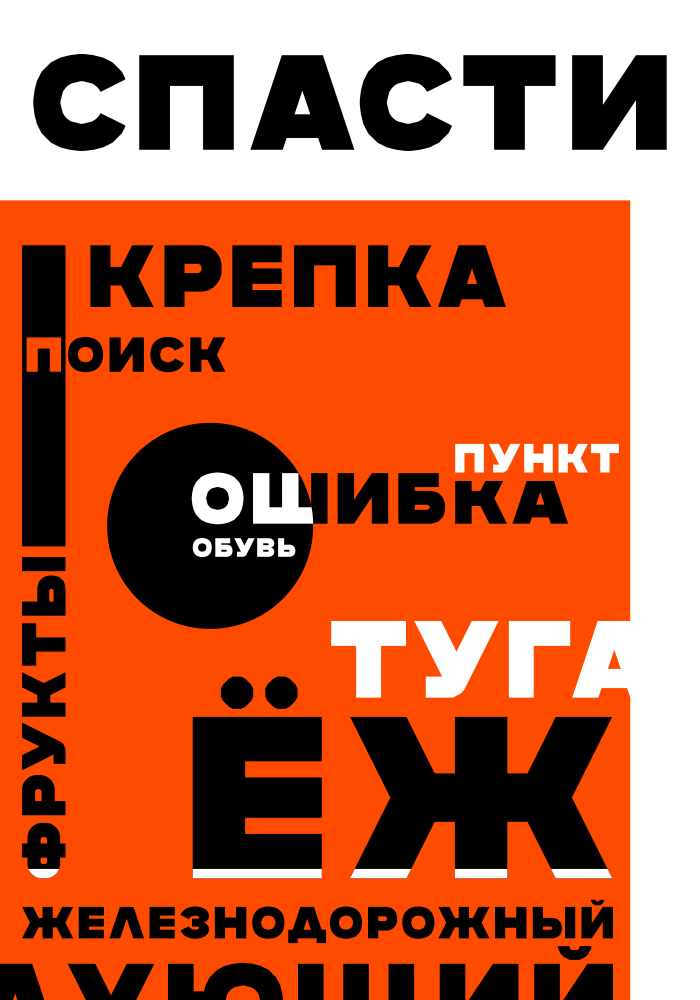
И СОХРАНИТЬ - (точнее спати и сохрани) - самая частая молитва к богу у православных (в России их много).
Я этот фильм ещё не смотрел, кстати, думаю стоит. А по шрифту - он мне очень напоминает Gotham, и чуть-чуть Proxima Nova. Но - да, он вполне конструктивистский, как и твой отличный плакат. Но крышка буквы П всё же нуждается в оптической компенсации на один пиксель - слишком сильно она выделяет и тянет вниз эту букву. Можно ещё придраться, что Ф не такая округлая, как З - но это уже придирки.
спасти
Я согласен о букве «П». Делаю ещё шрифт, в котором эта проблема и другие — исправлены. И он даже имеет латиницу.
Кстати, Dr. Dolittle не имеет ничего общего с Россией. Это просто факт, что я его посмотрел при создании этого шрифта)
Ты можешь создать латинские буквы? :)
Посмотри на «ALDRON». Оно улучшенный шрифт с латинскими буквами.
<Dmitriy Sychiov (Sychoff)> AND SAVE - (more precisely, sleep and save) - the most frequent prayer to God among the Orthodox (there are many of them in Russia).
I haven't seen this movie yet, but I think it's worth it. As for the font, it reminds me a lot of Gotham, and a little bit of Proxima Nova. But - yes, it is quite constructivist, like your excellent poster. But the cover of the letter P still needs optical compensation by one pixel - it highlights too much and pulls down this letter. You can still find fault with the fact that F is not as round as Z - but this is already nitpicking.
<TH3_C0N-MAN> I agree about the letter "P". I am making another font in which this problem and others are fixed. And it even has a Latin alphabet.
By the way, Dr. Dolittle has nothing to do with Russia. It's just a fact that I looked at it when creating this font)
<JayAndrewBoy> Can you create latin letters?
<TH3_C0N-MAN> Look at ALDRON. It is an improved font with Latin letters.